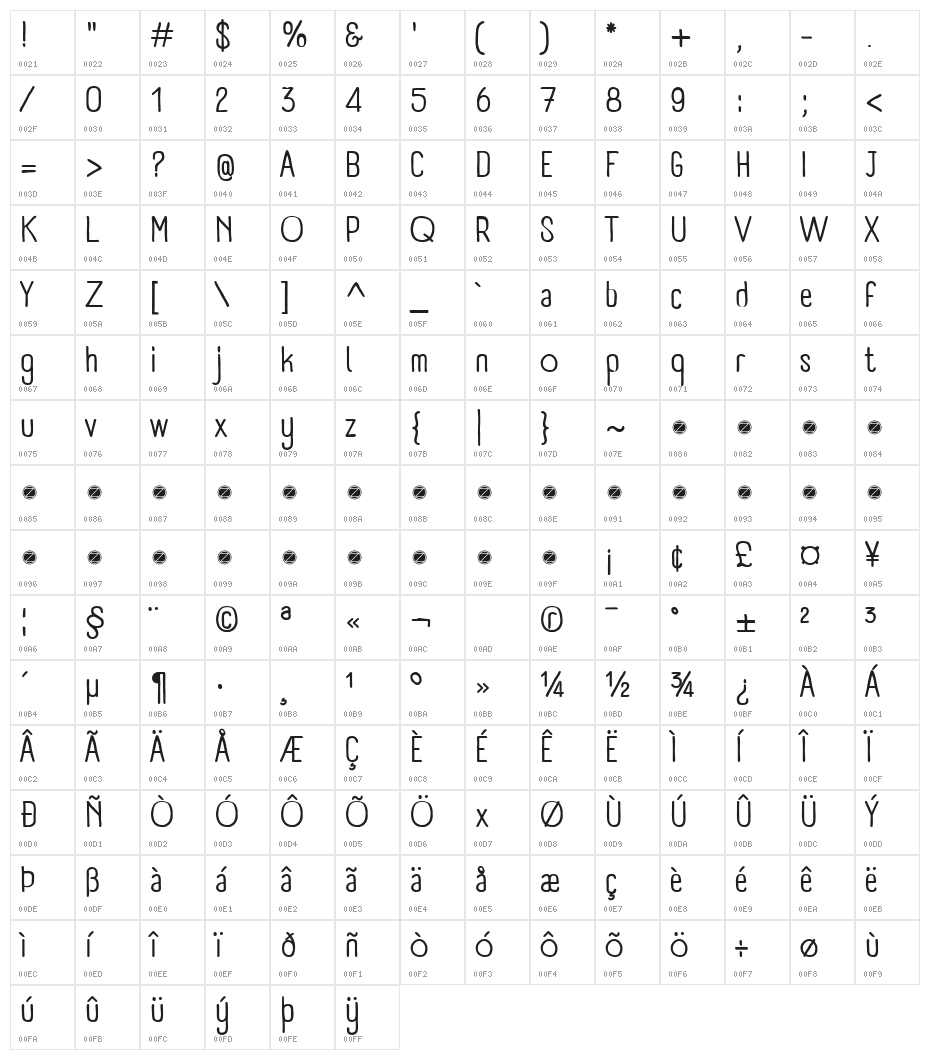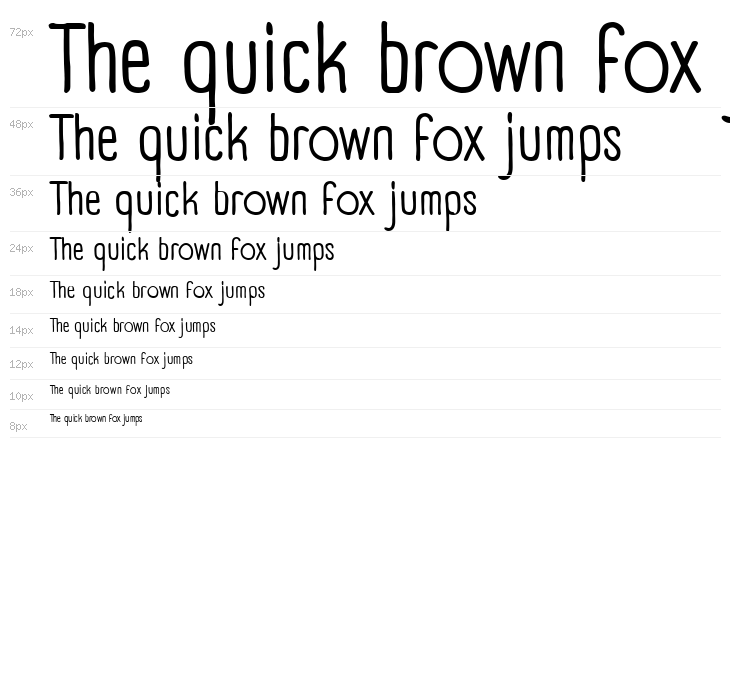
Panforte Pro Font
| Gesamtstil | Casual |
| Anwendungsfall | Headlines, Logos, Informal Text |
| Vorgeschlagene Projekte | Ideal for children's books, casual branding, playful posters, and friendly web design. |